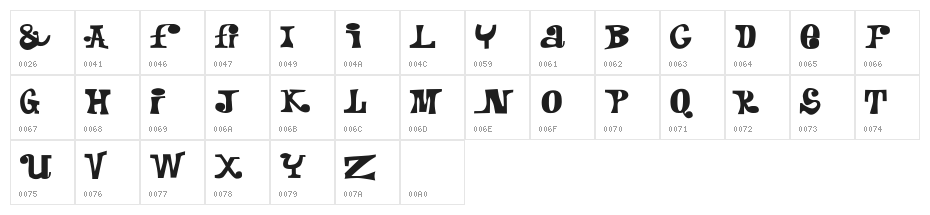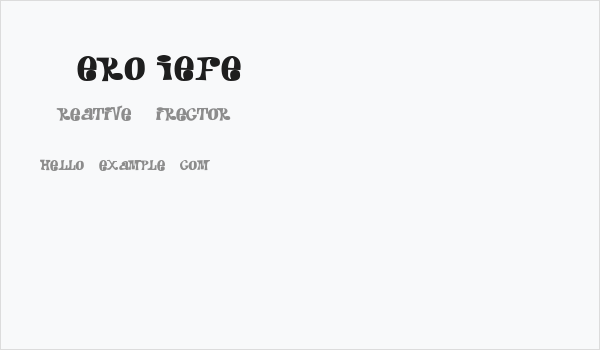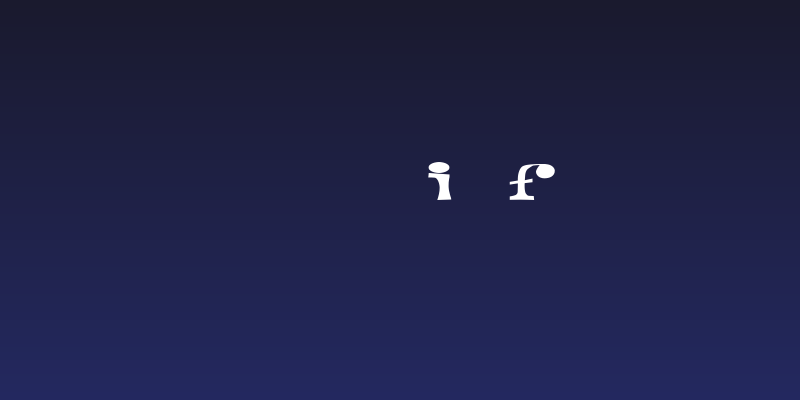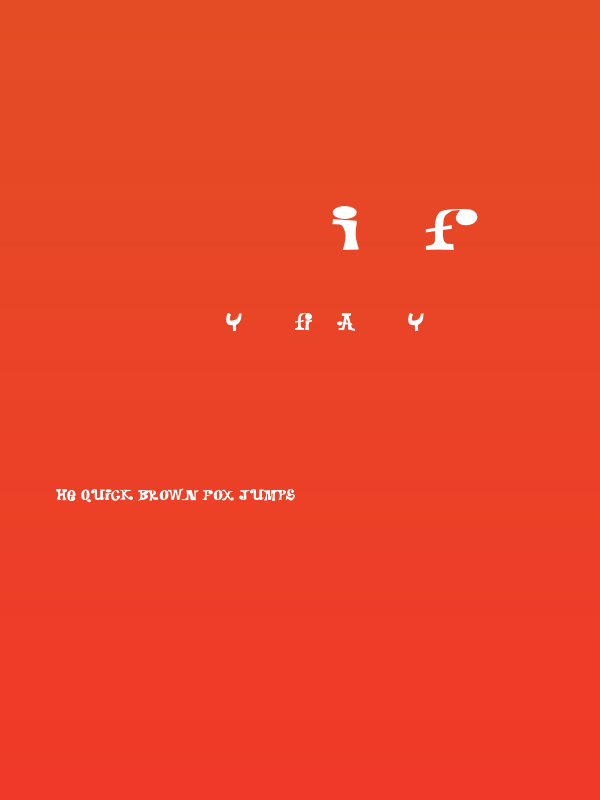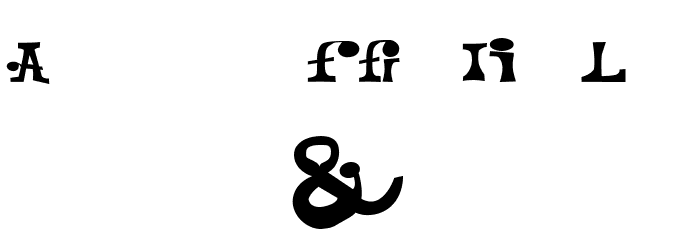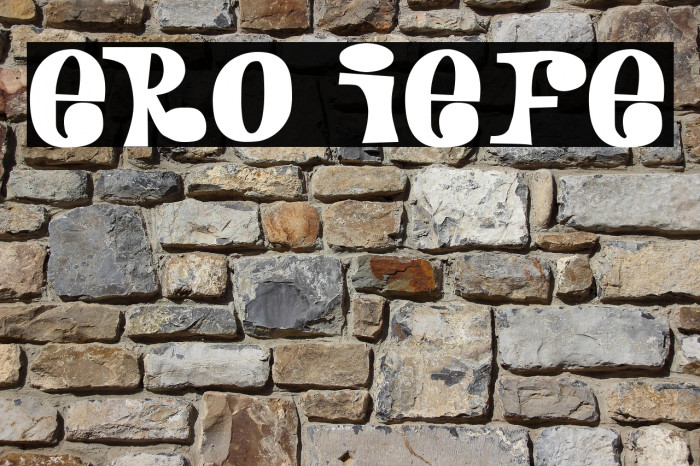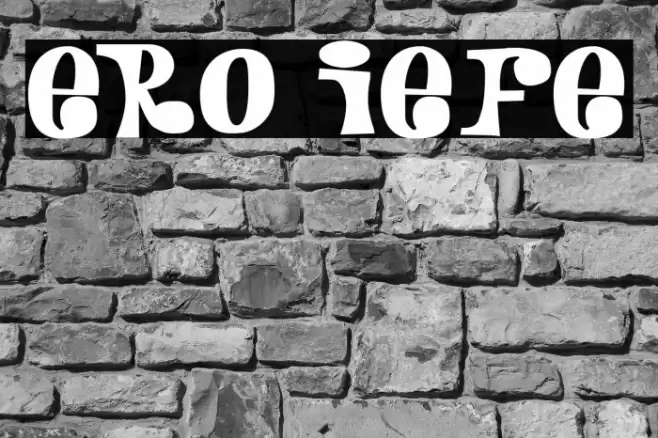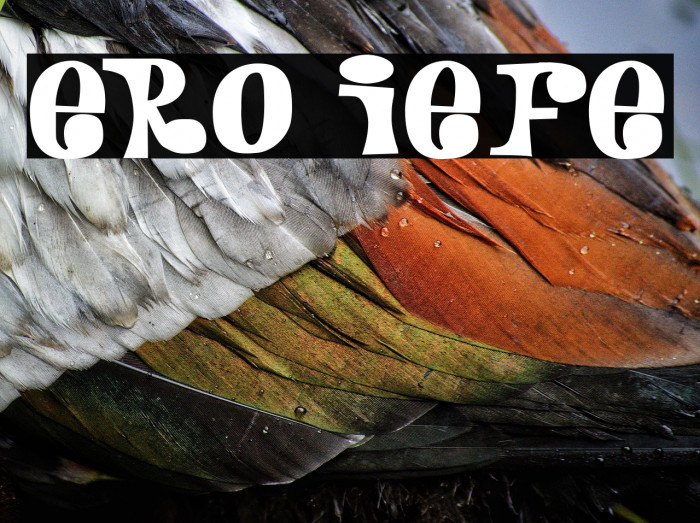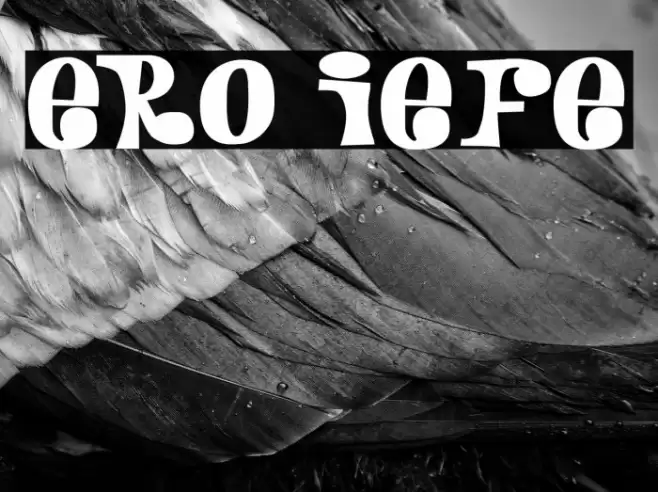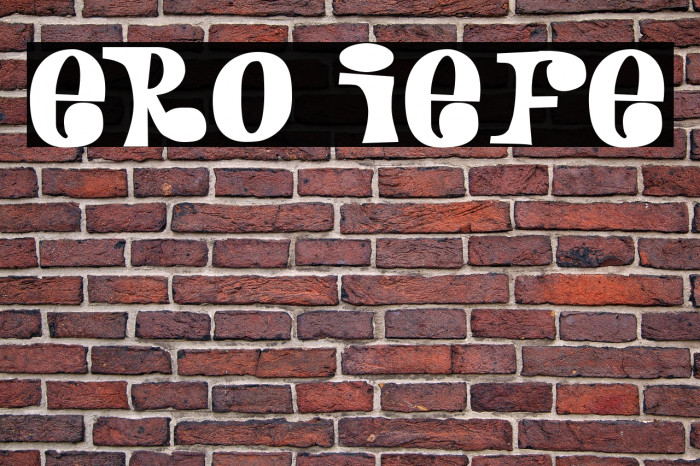
Pero Jefe Font
| Stile generale | Playful, Whimsical |
| Progetti proposti | Ideal for children's books, playful branding, posters, and creative design projects. |